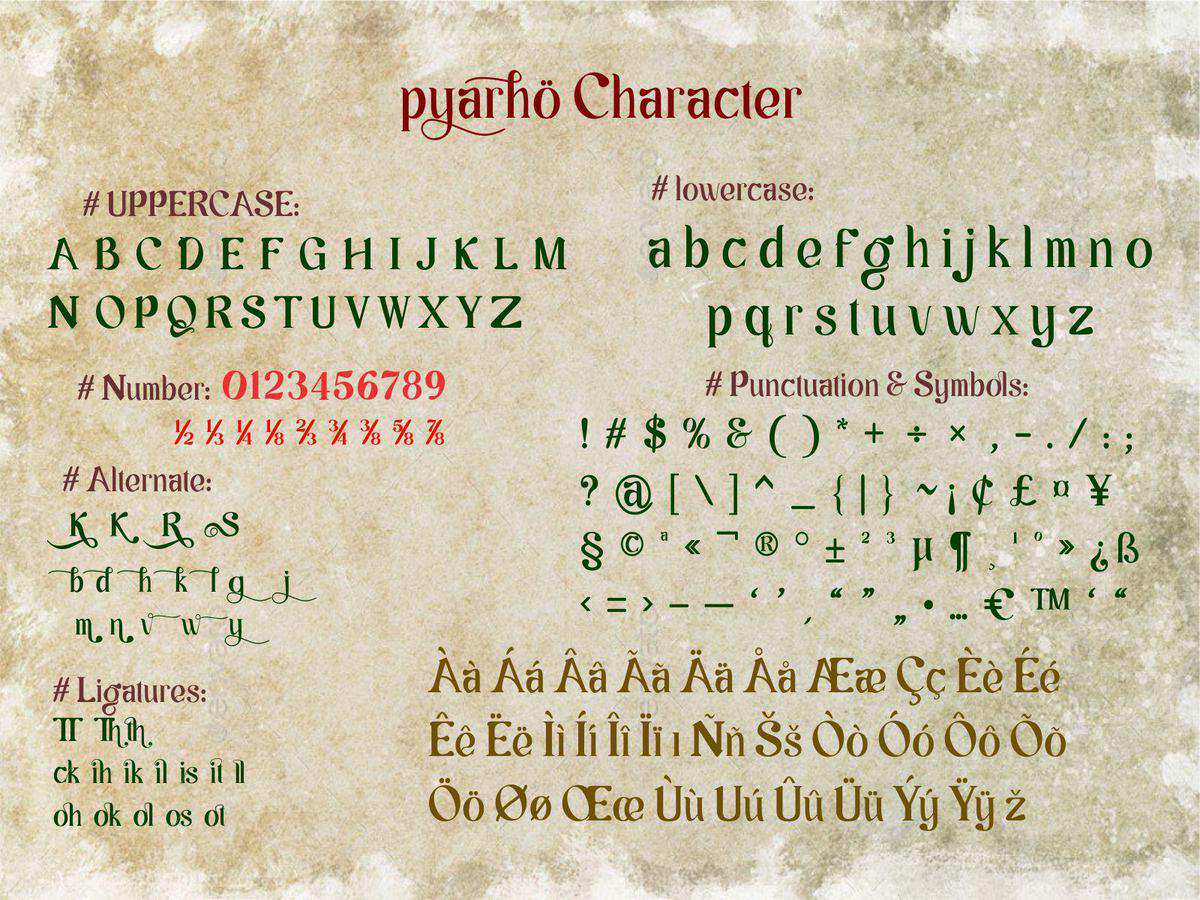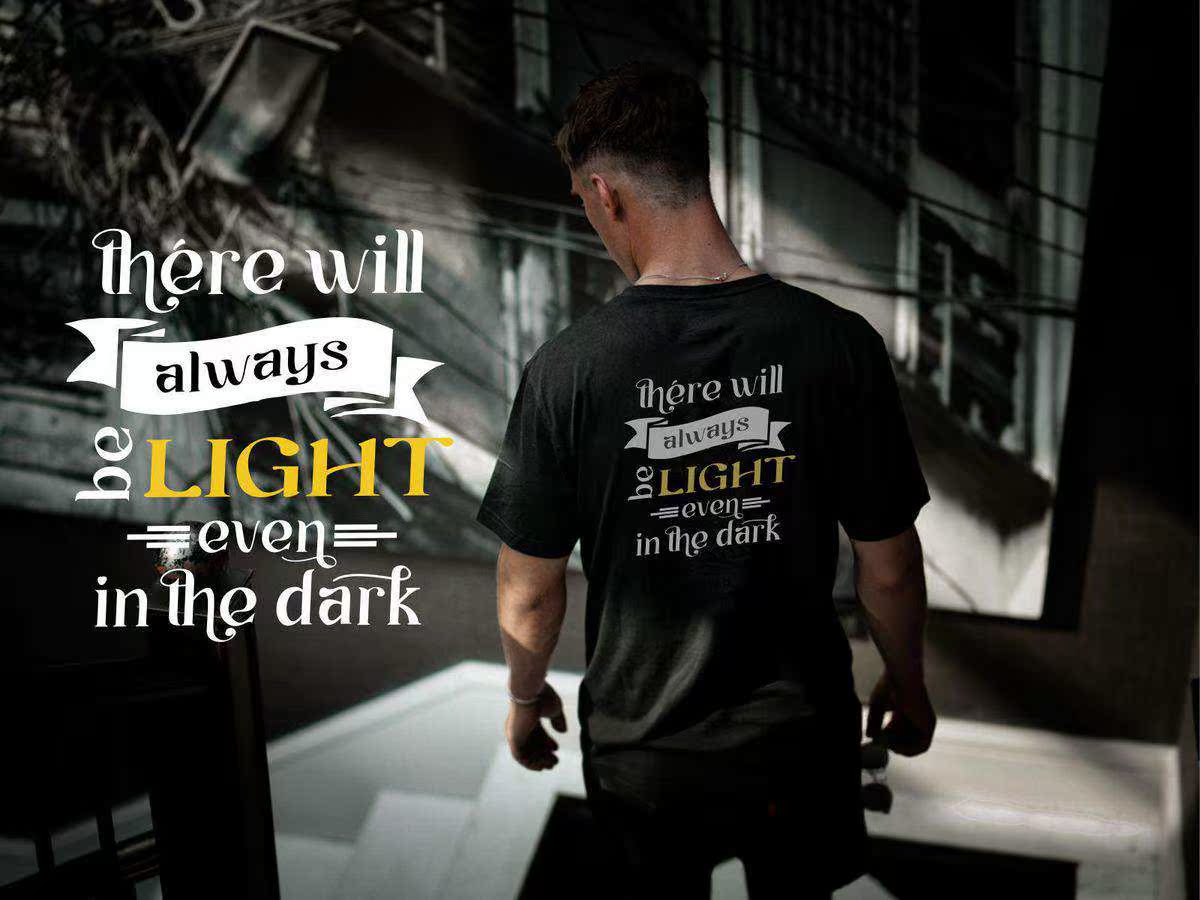
PyarhodadalahFontserifgayaModern.DibuatuntukemenyempurnakeandsainandDendangemaRegularModern,PyarhodadalahFontserifgayaModern.DibuatuntukemenyempurnakeandsainandDendangemaRegularModern,